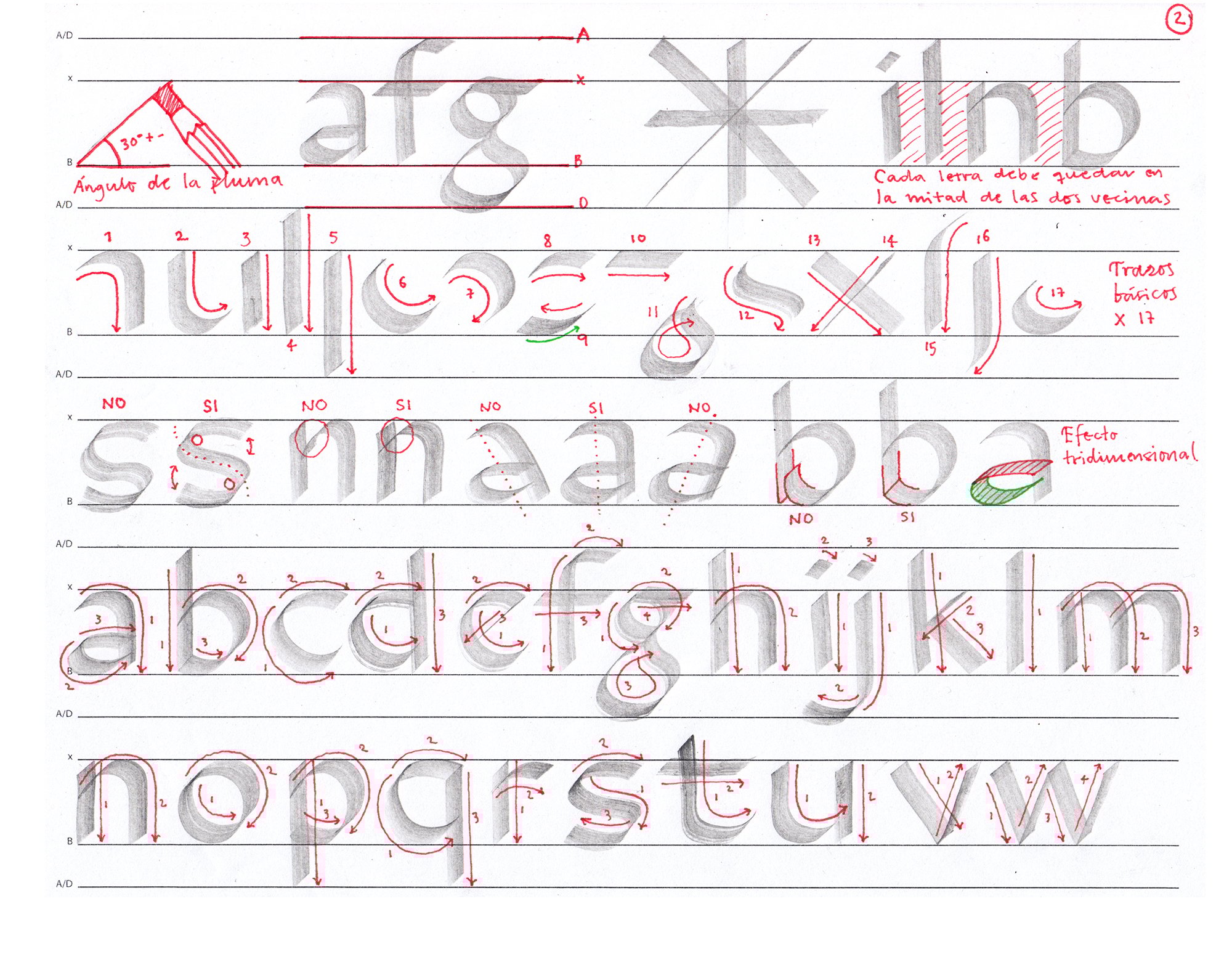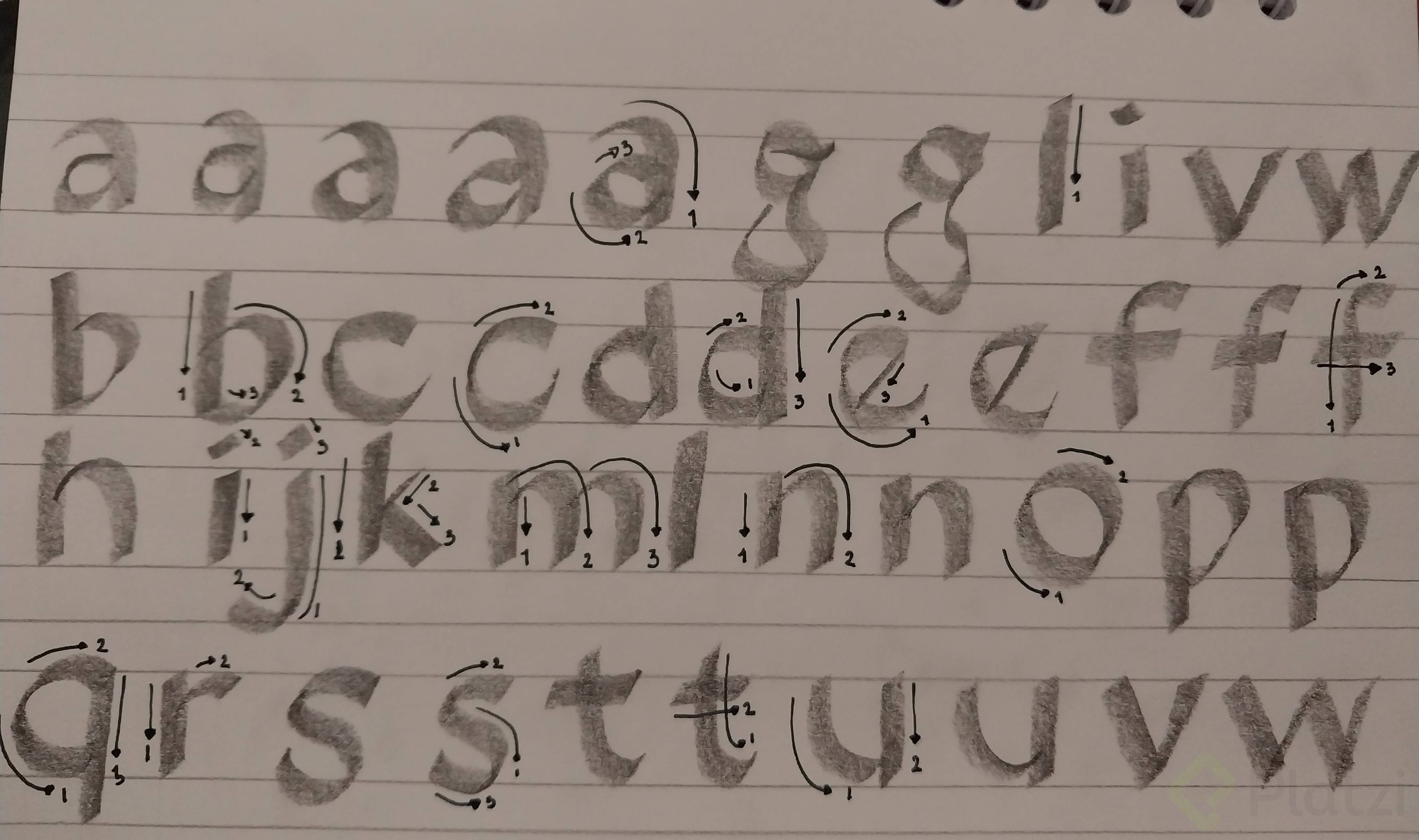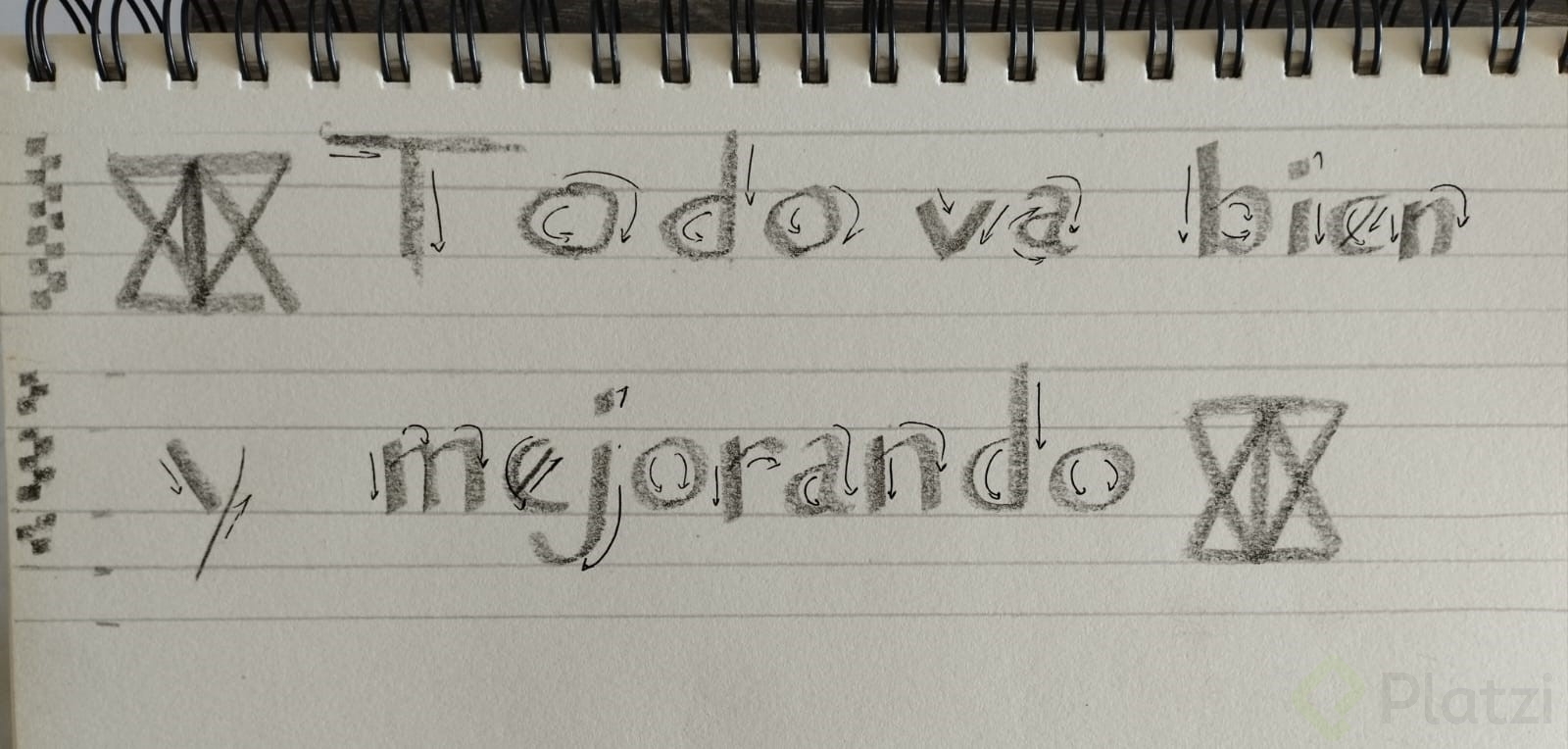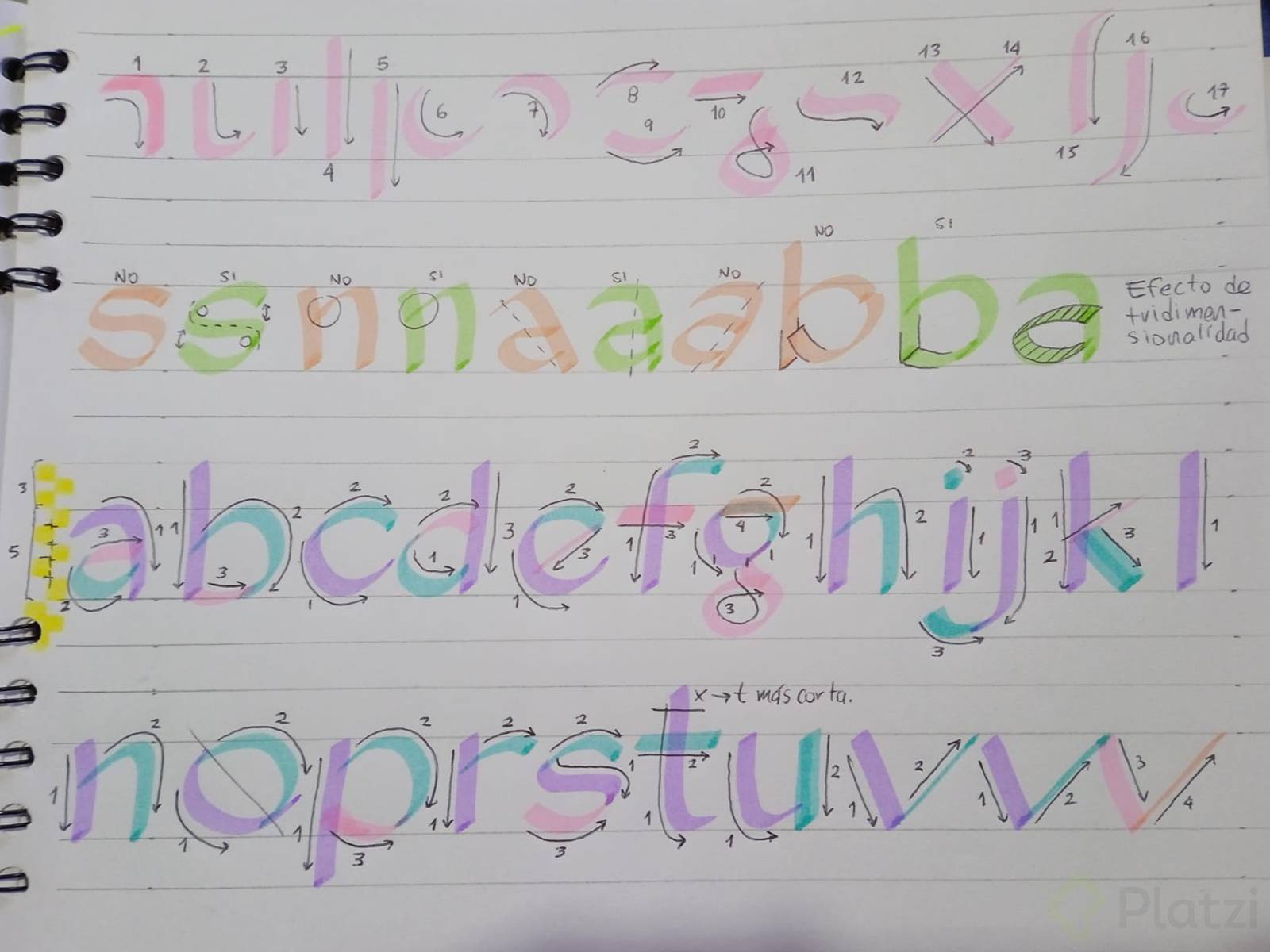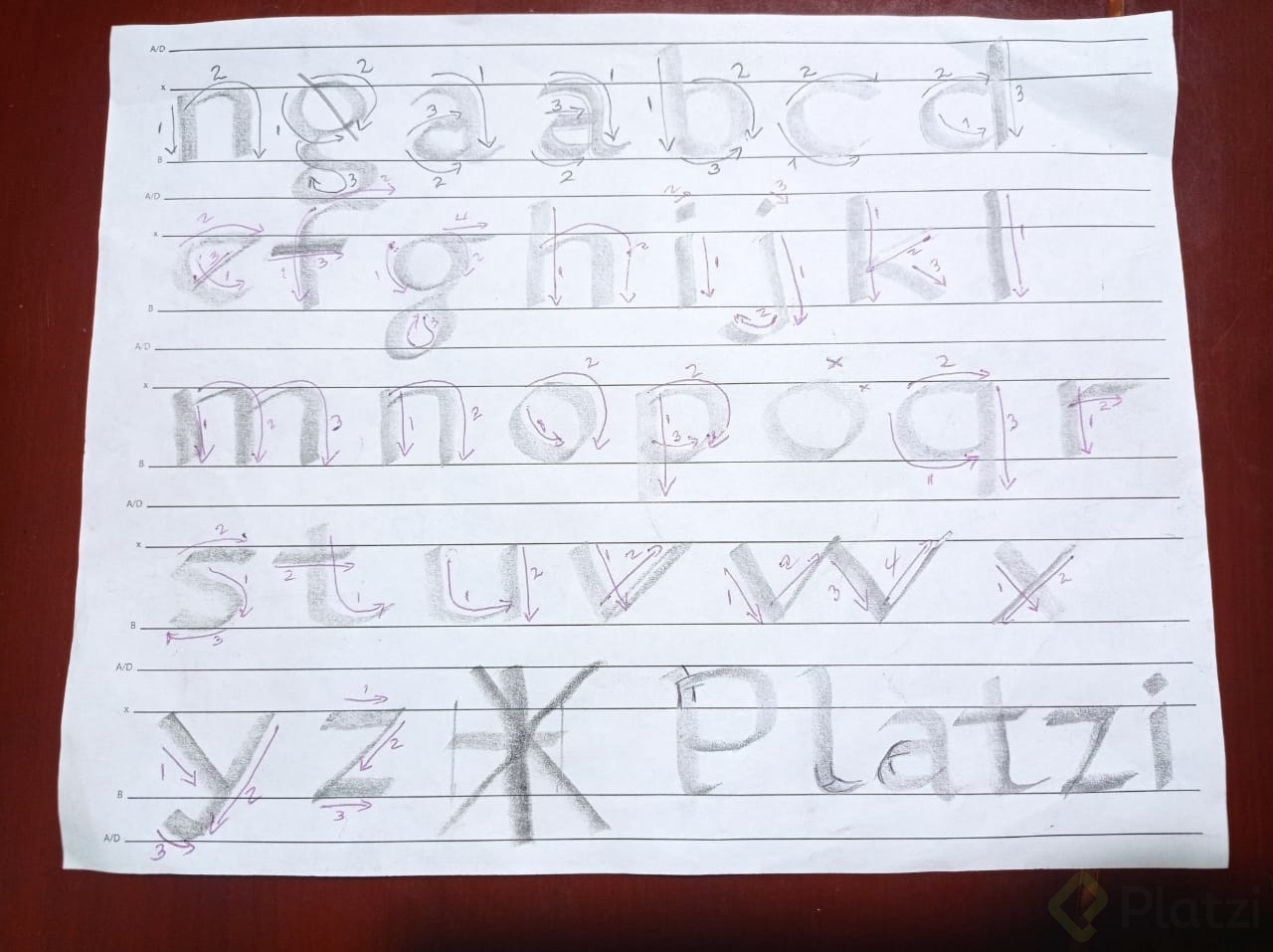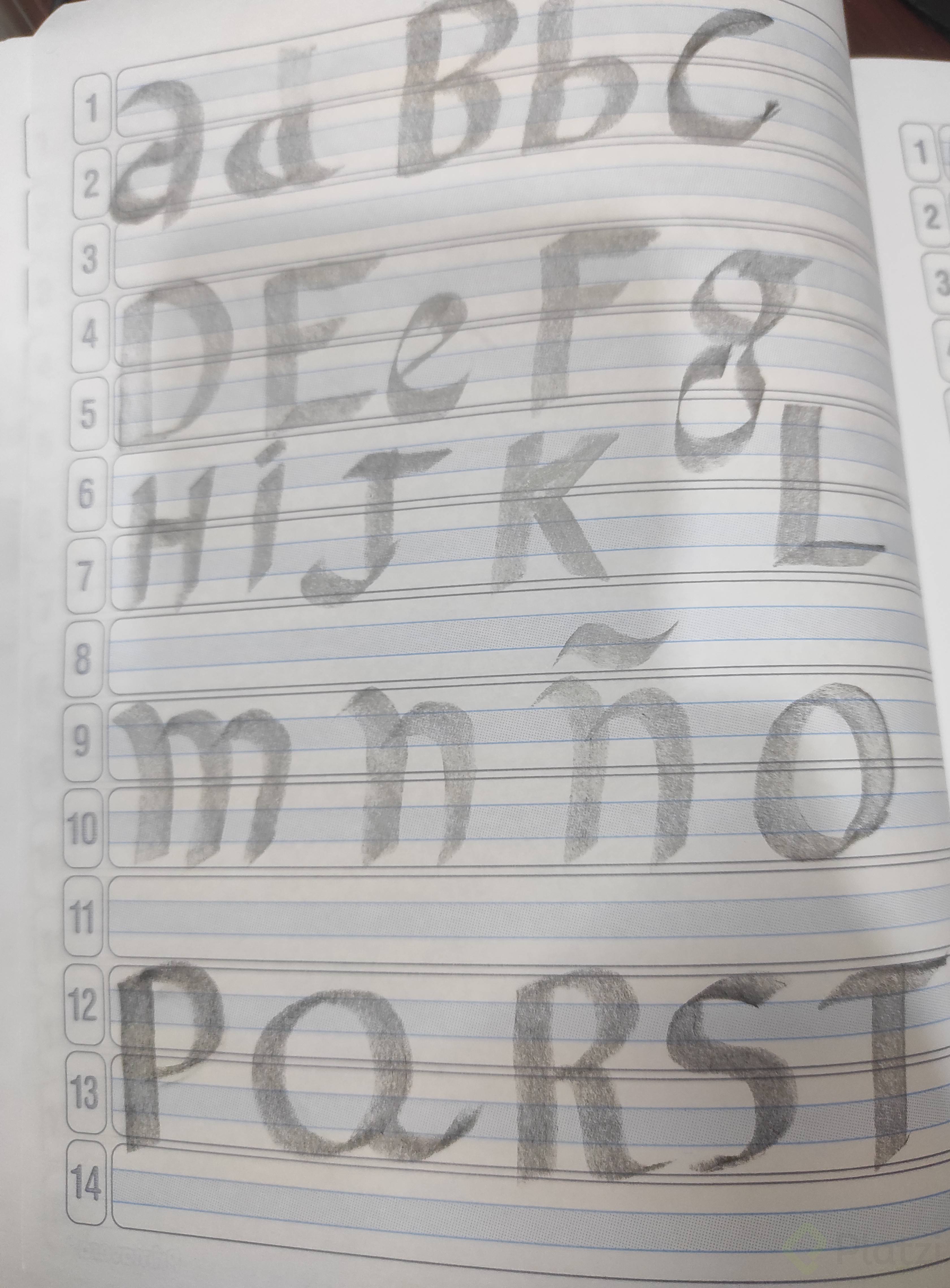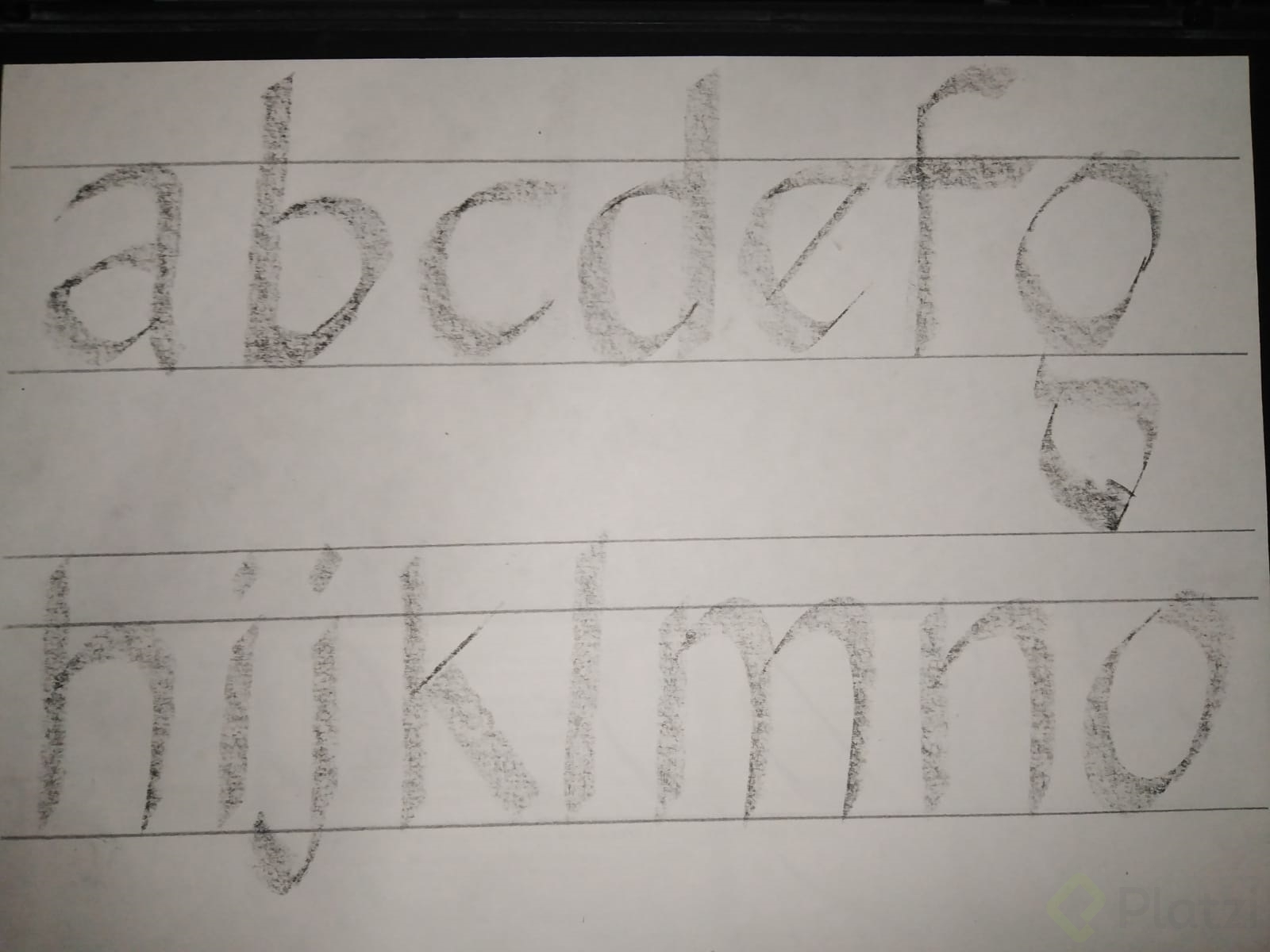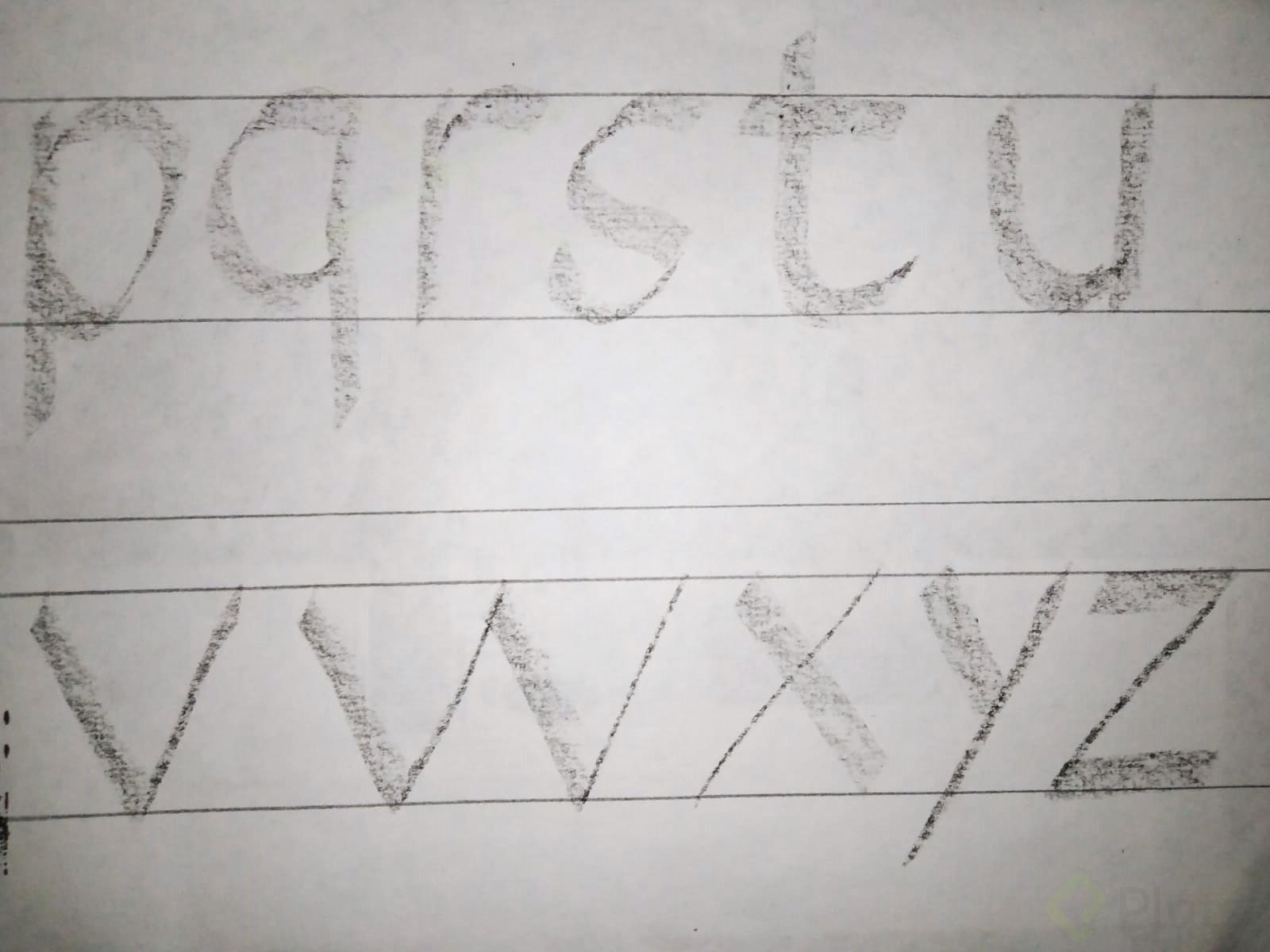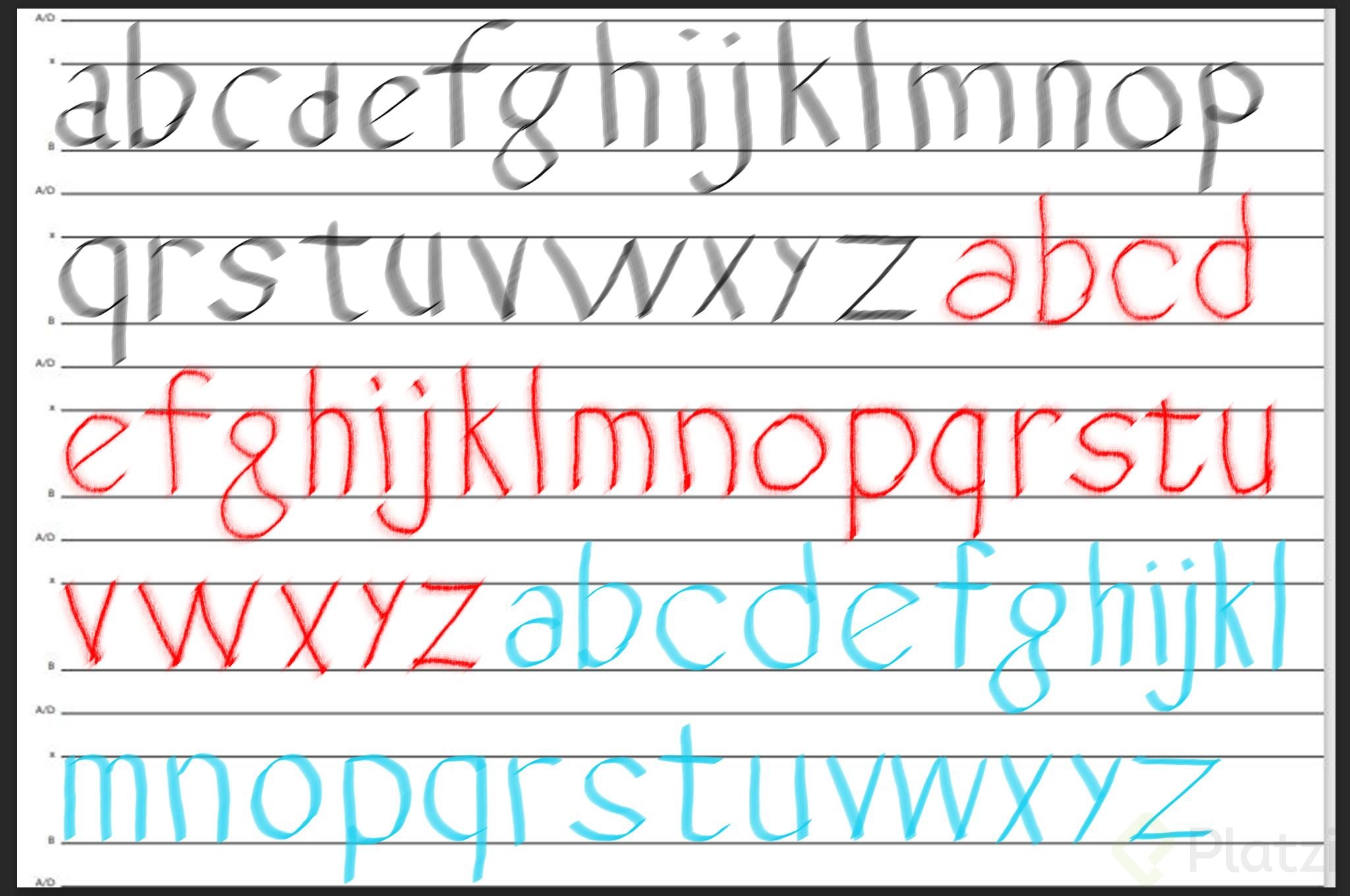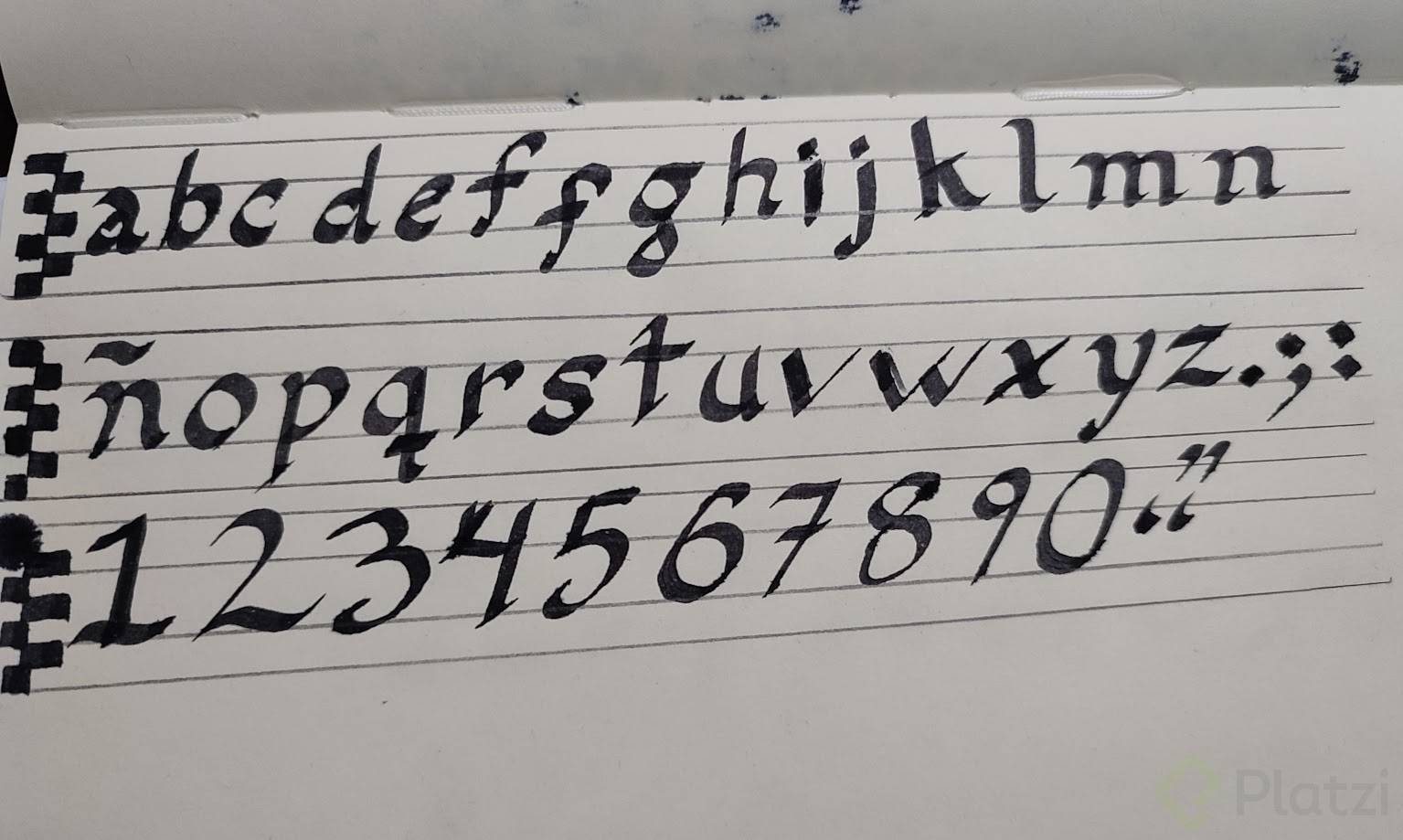
Caligrafía Fundacional: Trazos y Técnicas Básicas
Resumen
¿Cómo construir letras usando el ductus caligráfico?
El ductus caligráfico es el orden secuencial de trazos que forma cada letra.
La caligrafía fundacional la creó Edward Johnston a inicios del siglo XX.
Fue un artesano británico considerado junto con Rudolf Koch el padre de la caligrafía moderna.
Lo creó como base para poder hacer estilos caligráficos más complejos.
- Ejemplo: Letra "E"
- Trazos requeridos: 6, 8, 14.
- Secuencia:
- Realiza el trazo 6 como base.
- Añade el trazo 8 para el brazo medio.
- Completa con el trazo 14 para la barra inferior.
Ejercicio mental: Identificación de tipos de trazos
Antes de practicar, identifica los diferentes tipos de trazos que componen las letras. Este análisis te ayudará a comprender sus estructuras:
- Trazos ascendentes: Presentes en D, H, K, L.
- Trazos descendentes: Comunes en Q, P, J.
- Letras sin ascendentes ni descendentes: Como A, C, E, N, M, que se ajustan a la altura de la X.
Ejemplo práctico: Letras "A" y "G"
-
Letra "A":
- Requiere trazos 1, 17 y 8.
- Orden:
- Traza el hombro (trazo 1).
- Añade la barriga (trazo 17).
- Completa con el trazo curvo inferior (trazo 8).
-
Letra "G":
- Necesita trazos curvos y horizontales.
- Empieza con un trazo curvo para el cuerpo y sigue con los trazos horizontales para completar la forma.
Enfoques prácticos para mejorar la caligrafía
- Uso de plumas caligráficas variadas: experimenta con diferentes anchos de punta para entender cómo afectan el trazo.
- Variedad en módulos: practica letras condensadas o expandidas modificando el espacio horizontal entre trazos.
- Colores en el ductus: usa diferentes colores para identificar y memorizar cada trazo.
- Ejemplo: amarillo mostaza para el trazo 1, rojo para el trazo 2, etc.
Ejercicio práctico: Análisis completo de trazos
Aa:
- Trazos:
- Curvo (para la parte redondeada de la letra).
- Altura de X (se desarrolla en el espacio medio).
- Vertical (para el trazo recto de soporte).
Bb:
- Trazos:
- Ascendente (el trazo vertical que sobrepasa la altura de la X hacia las mayúsculas).
- Curvo (forma la barriga de la letra).
- Altura de X (se acomoda en el espacio medio).
- Vertical (trazo recto que conecta el cuerpo).
Cc:
- Trazos:
- Curvo (la forma abierta de la letra).
- Altura de X (se sitúa completamente en el espacio medio).
Dd:
- Trazos:
- Ascendente (el trazo vertical que se extiende hasta la altura de las mayúsculas).
- Curvo (para formar la barriga de la letra).
- Altura de X (el cuerpo se desarrolla en esta área).
- Vertical (para conectar la estructura).
Ee:
- Trazos:
- Curvo (para la parte abierta superior e inferior).
- Altura de X (el trazo se desarrolla completamente en este espacio).
Ff:
- Trazos:
- Ascendente (el trazo vertical que sobrepasa la altura de la X).
- Horizontal (la barra superior que cruza la letra).
- Vertical (el trazo que forma la base).
Gg:
- Trazos:
- Descendente (el trazo que cae por debajo de la línea base).
- Curvo (para la forma redondeada principal).
- Horizontal (la línea que cierra la letra en su interior).
Hh:
- Trazos:
- Ascendente (trazo vertical que alcanza la altura de las mayúsculas).
- Vertical (el soporte paralelo al trazo ascendente).
- Curvo (la conexión o barra entre los dos trazos verticales).
Ii:
- Trazos:
- Vertical (un trazo recto, sin adiciones decorativas).
Jj:
- Trazos:
- Vertical (se extiende hacia la línea base).
- Descendente (el trazo que cae por debajo de la línea base).
- Curvo (la terminación inferior).
Kk:
- Trazos:
- Ascendente (trazo vertical que alcanza la altura de las mayúsculas).
- Vertical (la estructura principal).
- Curvo (para los brazos de la K).
Ll:
- Trazos:
- Ascendente (un trazo largo y recto que alcanza la altura de las mayúsculas).
- Vertical (estructura principal).
Mm:
- Trazos:
- Curvo (las partes redondeadas inferiores).
- Altura de X (toda la letra se desarrolla dentro de este espacio).
- Vertical (los trazos rectos de soporte).
Nn:
- Trazos:
- Curvo (la transición suave entre trazos).
- Altura de X (la letra se ajusta completamente aquí).
- Vertical (las líneas rectas de soporte).
Oo:
- Trazos:
- Curvo (la forma completamente redondeada).
- Altura de X (se ajusta a este espacio sin ascensos ni descensos).
Pp:
- Trazos:
- Descendente (el trazo que cae por debajo de la línea base).
- Curvo (para formar la barriga).
- Vertical (estructura principal).
- Altura de X (la parte superior se ajusta a este espacio).
Qq:
- Trazos:
- Descendente (el trazo que baja por debajo de la línea base).
- Curvo (para formar la parte redonda principal).
- Vertical (estructura principal).
- Altura de X (la parte superior se ajusta aquí).
Rr:
- Trazos:
- Altura de X (toda la letra se ajusta dentro de este espacio).
- Vertical (estructura recta principal).
Ss:
- Trazos:
- Curvo (la forma serpenteante de la letra).
- Altura de X (se desarrolla completamente en este espacio).
Tt:
- Trazos:
- Ascendente (el trazo vertical que alcanza la altura de las mayúsculas).
- Vertical (estructura principal).
- Horizontal (la barra transversal).
- Curvo (opcional para detalles decorativos).
Uu:
- Trazos:
- Curvo (parte inferior redondeada).
- Altura de X (la letra se ajusta a este espacio).
- Vertical (los extremos de la estructura).
Vv:
- Trazos:
- Altura de X (la letra se desarrolla completamente aquí).
Ww:
- Trazos:
- Altura de X (se ajusta completamente al espacio medio).
Consejos adicionales para la práctica
- Orden: sigue el ductus estrictamente para desarrollar precisión.
- Repetición: practica cada letra varias veces hasta lograr uniformidad.
- Observación crítica: analiza cómo se comportan los trazos en relación con las líneas guía.
- Variedad: cambia herramientas y ángulos para explorar diferentes estilos.